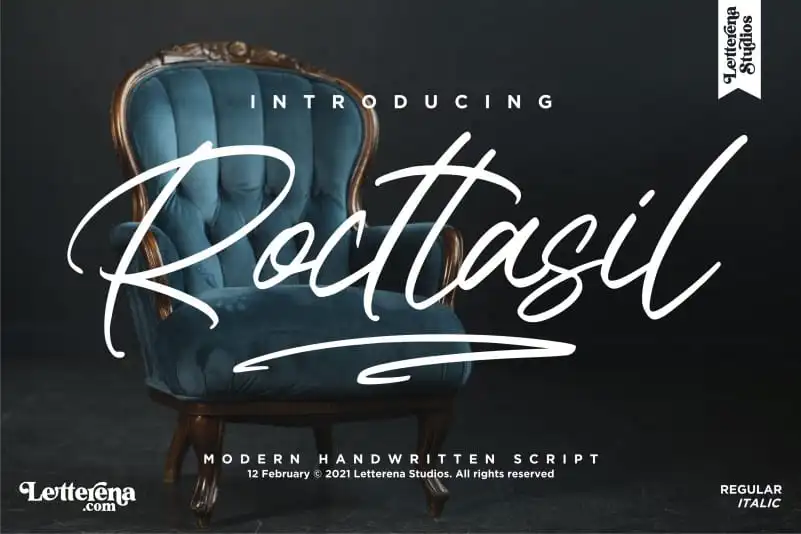
Rocttasil Script Font – Download Grátis
A ‘Rocttasil Script Font’ é uma herança dos tempos das cartazes elegantes que você pode encontrar no papel de parede antigo ou na capa de um livro delicado de estilo art déco. Desenvolvida pela Letterena, ela carrega consigo o encanto da caligrafia romântica, perfeita para qualquer projeto que busque trazer elegância e sofisticação, seja em uma identidade visual de marca, design de mobília ou até mesmo em um pacote de produto. Suas linhas curvas e delicadas são perfeitamente adaptáveis a designs como assinaturas de logotipos, marcas de produtos, cartões de convite e até mesmo aos detalhes dos rolos de papelão para sacolas de supermercado ou embalagens de café da manhã. Seja qual seja o projeto que você esteja desenvolvendo, ‘Rocttasil Script Font’ tem uma maneira única de torná-lo único, elevando-o a um nível superior de sofisticação e delicadeza. Não espere mais para incorporar essa fonte elegante e suave em seu próximo design.